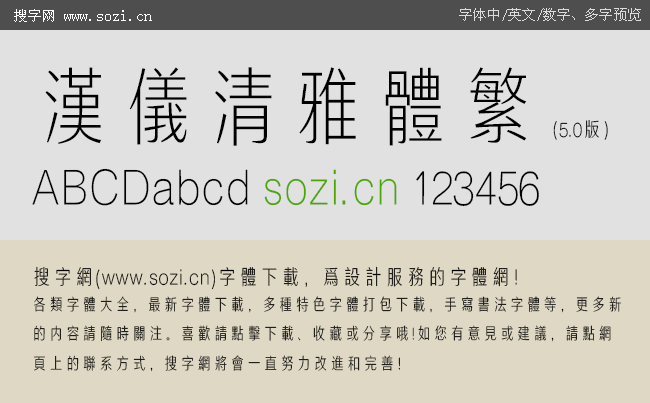
漢儀清雅體繁
搜字網(wǎng)提供一款漢儀清雅體繁中文字體下載,清雅體氣質(zhì)高挑,簡單的筆畫設(shè)計增加了字形的易讀效果,充滿彈性的弧度變化,在體現(xiàn)筆畫柔軟度的同時,表現(xiàn)出靈動、纖細的清新氣質(zhì),給使用者更加輕松愉悅的視覺感受。 常用于報刊雜志排版,也適用于平面廣告,圖書印刷等廣告設(shè)計場合使用。